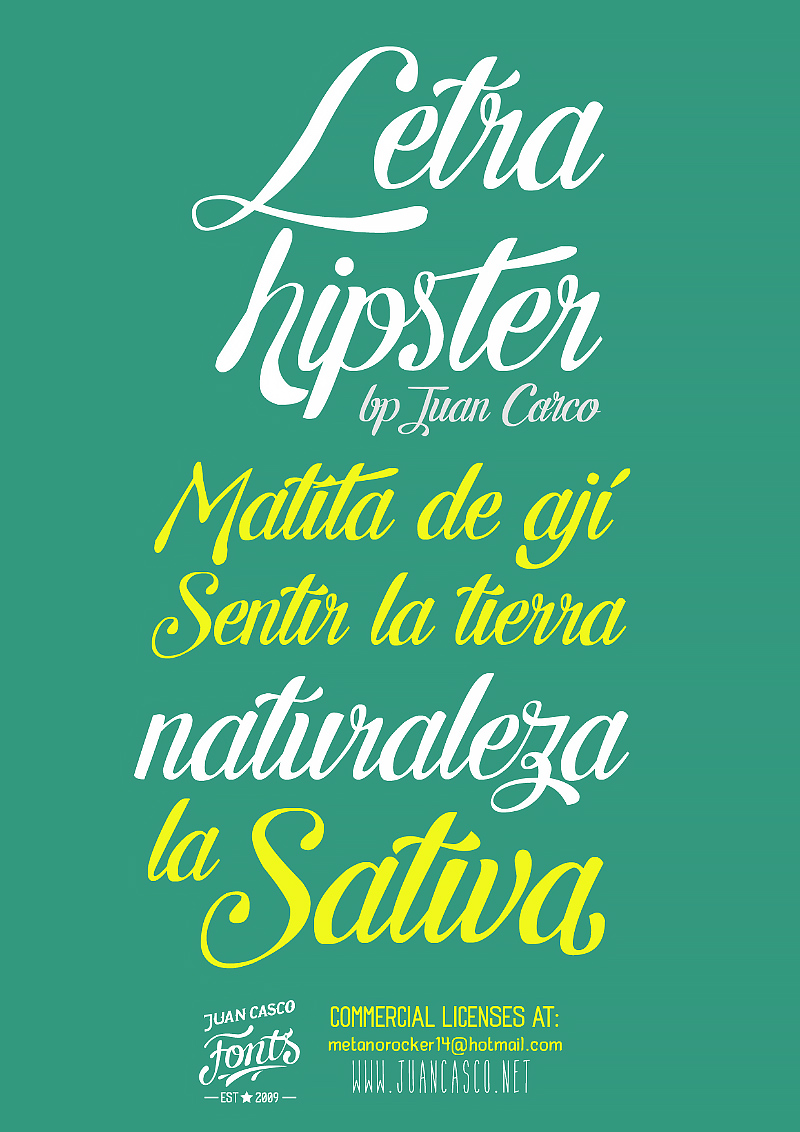
Дополнения Шрифты Татьяна Гапонова 23 октября 2017 Шрифт - Letra Hipster Классный каллиграфический шрифт для дизайна надписей. Формат - TTF. Размер - 0,2 мб. Скачать Шрифт - Letra Hipster